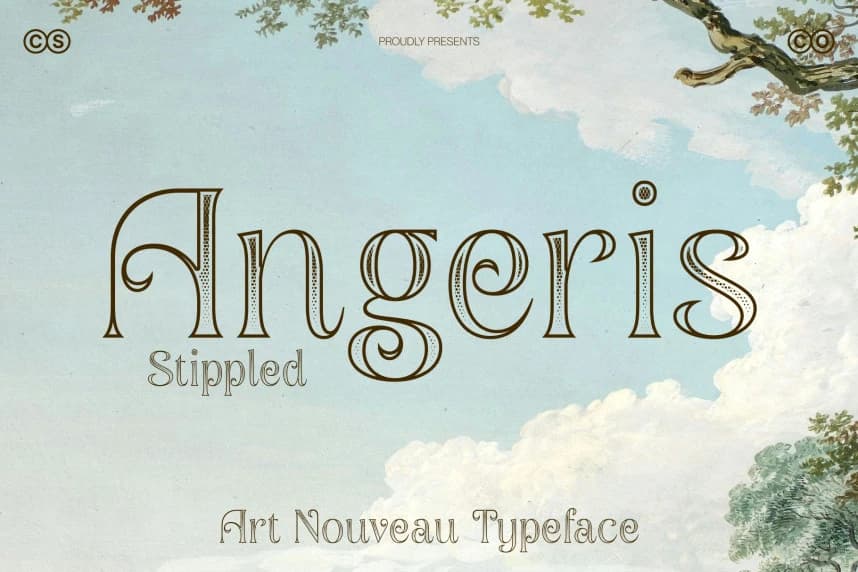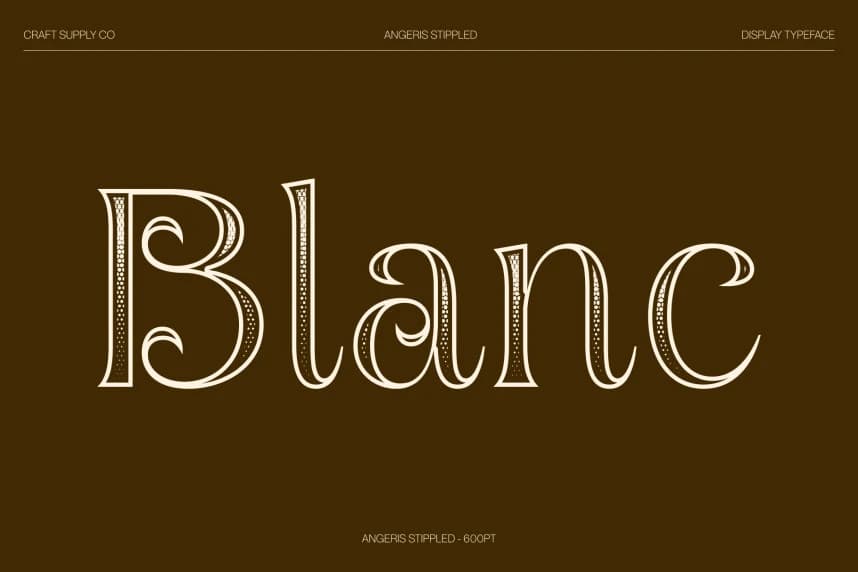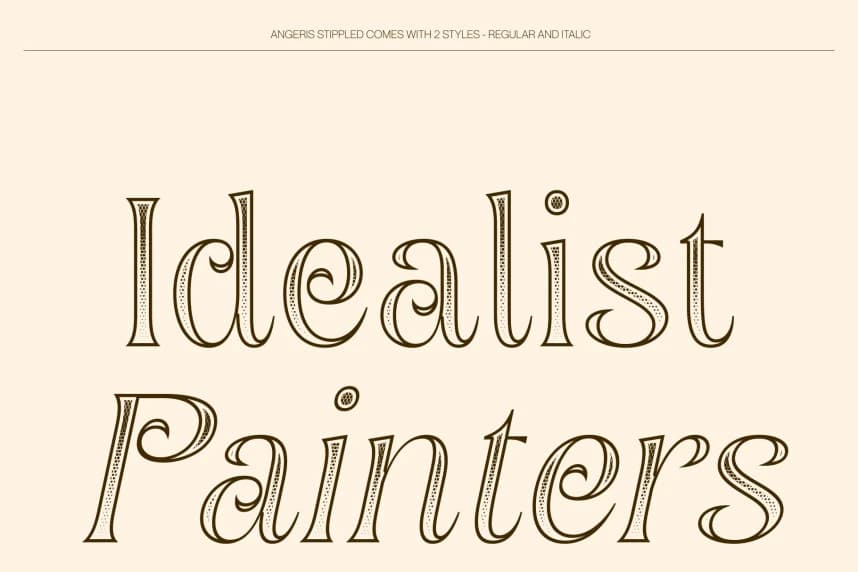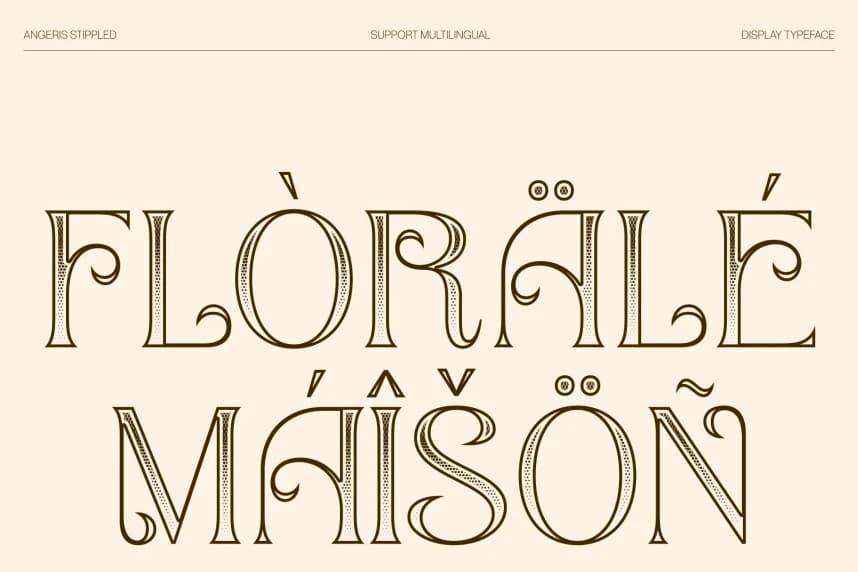
Angeris Stippled Font
Angeris Stippled Font – Retro Şıklığına Bir Selam. Retro Art Nouveau ile Stippled Sophistication. Bu tasarım, ikonik Art Nouveau hareketinden ilham alıyor ve zamansız nostaljiyi çağrıştıran retro bir çekicilikle zenginleşiyor.